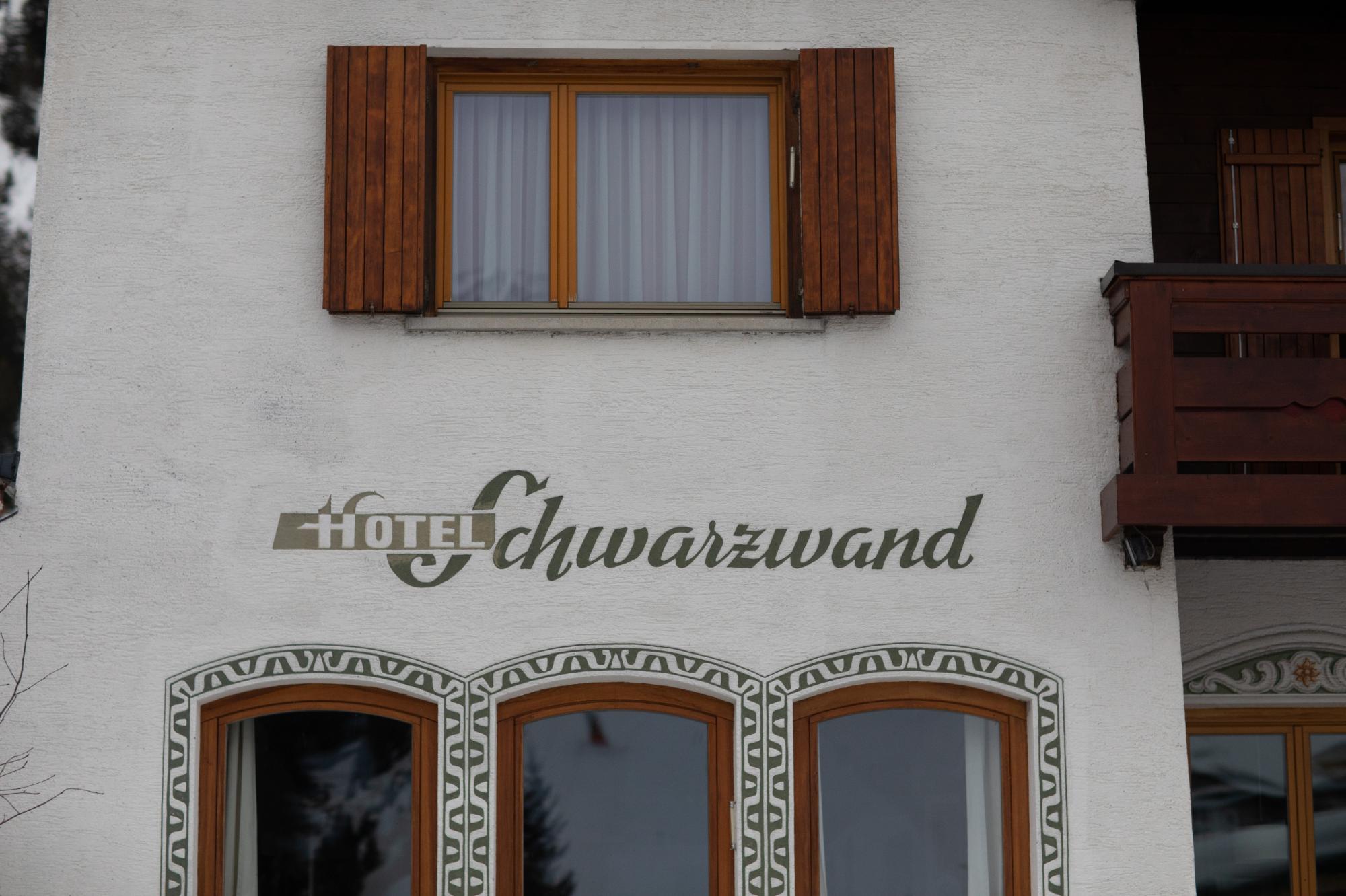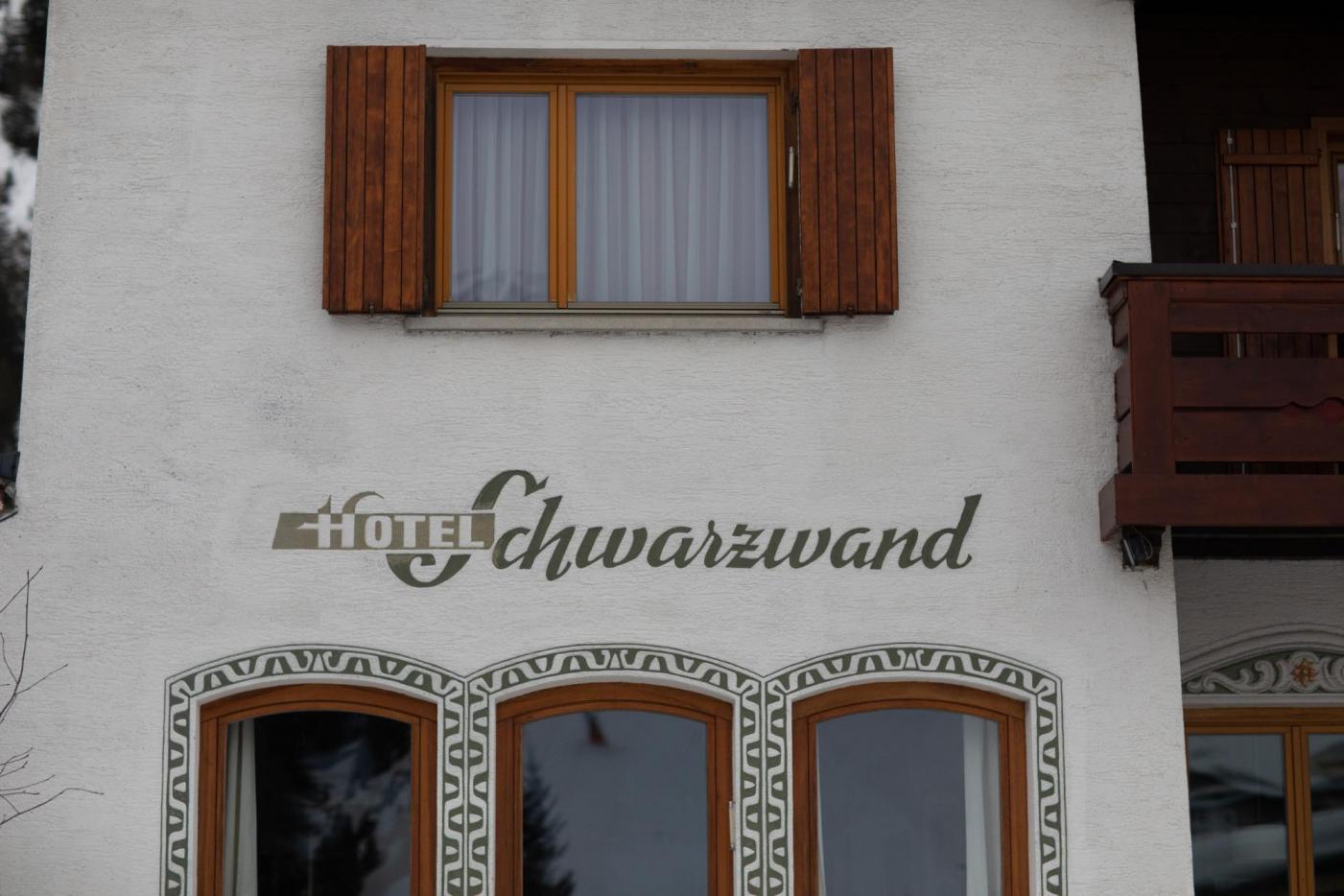
Suche Schriftart von Hausfassade (Hotel Schwarzwand)
Suche diesen oder sehr ähnlichen Font für einen unserer Kunden.
Die Schrift wurde vor einiger Zeit als Logo für einen Hotelkunden von uns auf der Fassade angebracht.
Für ein weiteres Projekt benötigen wir allerdings diese Schrift.
Der Kunde kann sich aber nicht mehr daran erinnern, welche Schrift es war und es gibt keine Infos dazu.
Es geht um den Schriftzug "Schwarzwand"
Zuerst dachte ich mir wie oft das wohl auf "Schwarzwald" korrigiert wird. Es ist aber in Österreich, also vielleicht nicht so oft 🙂
Im übrigen stimme ich Ralf zu, obwohl es auch sein kann, daß die Vorlage mit einer Schrift gemacht wurde, und die Variationen erst durch (schlampige) Umsetzung durch den Häusermaler entstanden.
Und dann sollte man auch wissen, was genau benötigt wird:
Benötigt man wirklich eine komplette Schrift, mit der man dann beliebige Texte verfassen möchte oder reicht eine saubere Digitalisierung des Logos, sodass man z.B. das Logo auf allen Drucksachen und/odr der Website des Hotels verwenden kann.
Im ersteren Fall, so die Vorlage tatsächlich vom Schildermaler gezeichnet wurde, würde bedeuten, dass man dann ja alle weiteren, im Wort Schwarzwand nicht vorhandenen Buchstaben hinzu gestalten müsste, wie ich es, auch für einen Fall in Österreich hier schon durchgezogen hatte: